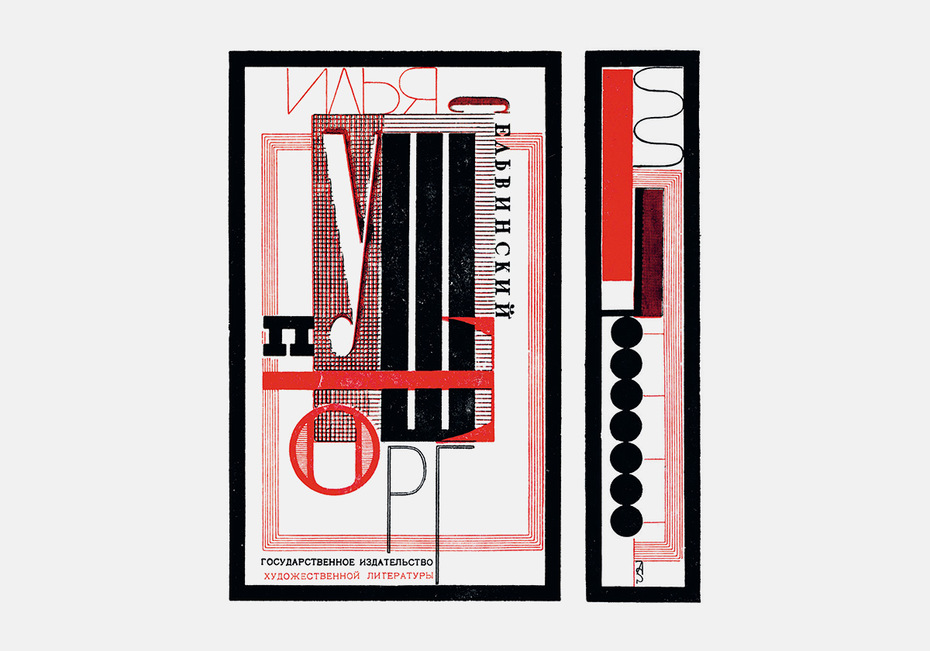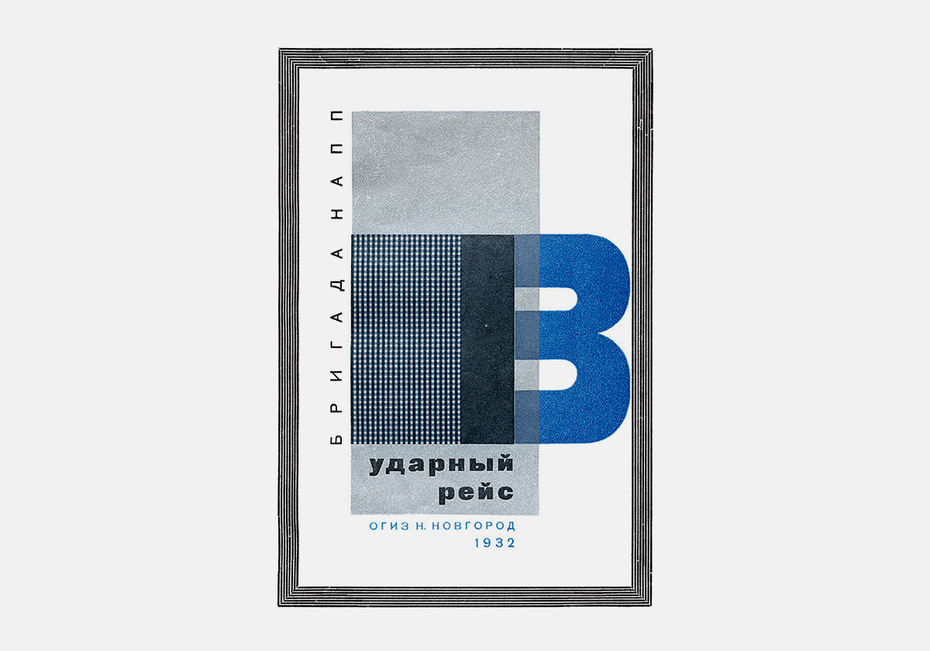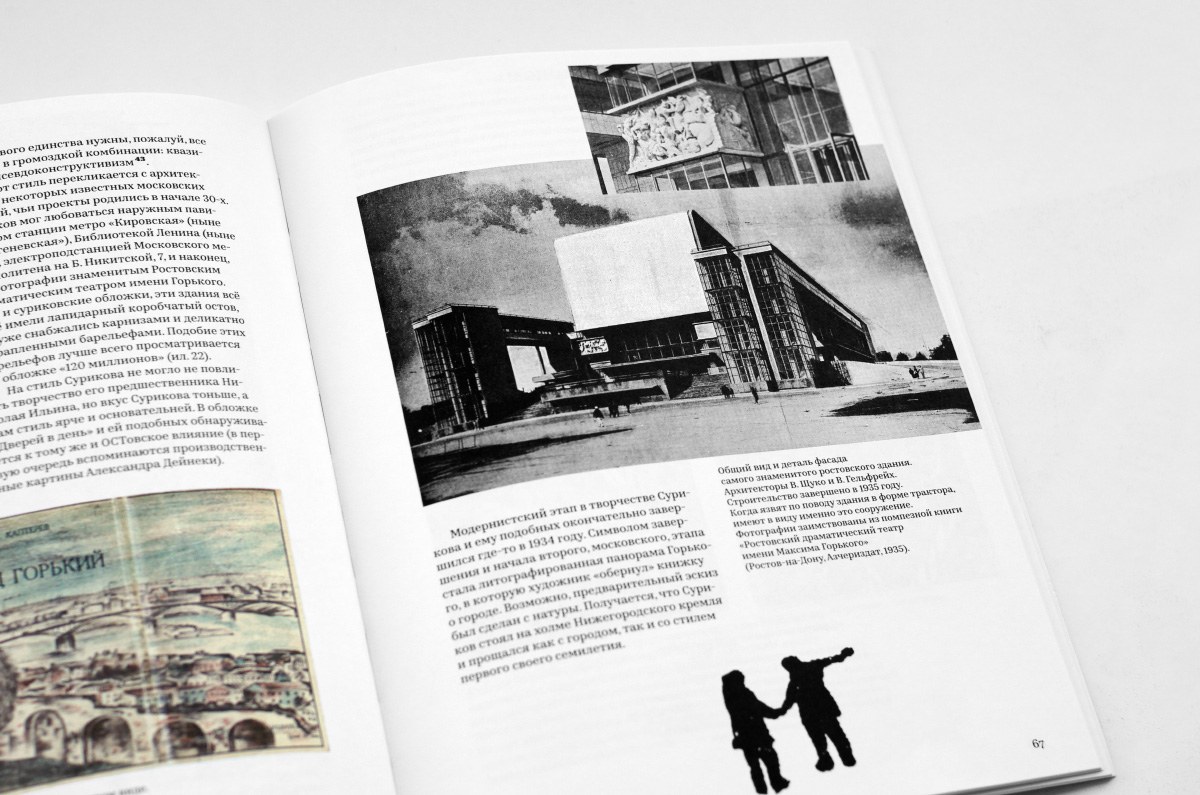
Стиль сан Су: о новой книге Владимире Кричевского
ла­ди­мир Кри­чев­ский от­крыл ещё од­ну звез­ду в пле­я­де гра­фи­че­ских ди­зай­не­ров два­дца­тых го­дов XX ве­ка. Но­вая мо­но­гра­фия по­свя­ще­на Алек­сан­дру Ми­хай­ло­ви­чу Су­ри­ко­ву (1907–1946) и про­дол­жа­ет се­рию книг о ди­зай­не­рах «дца­тых», в ко­то­рой В. К. уже рас­ска­зал о Ни­ко­лае Ильи­не, Кон­стан­ти­не Бор-Ра­мен­ском, Дмит­рии Бу­ла­но­ве.
Вни­ма­тель­ные чи­та­те­ли вспо­мнят, что Су­ри­ков по­яв­лял­ся в по­ле вни­ма­ния Кри­чев­ско­го ра­нее — в кни­ге об Ильи­не ему бы­ла по­свя­ще­на от­дель­ная гла­ва «По­сле Ильи­на, или AS» и по­ка­за­но при­лич­ное ко­ли­че­ство об­ло­жек, сде­лан­ных Су­ри­ко­вым в по­ру ра­бо­ты в Ниж­нем Нов­го­ро­де в пер­вой по­ло­ви­не 30-х. В этой гла­ве уже про­яв­лен ин­те­рес к сти­лю ди­зай­не­ра, ко­то­рый (стиль) был на­зван «ар-де­ко со­вет­ско­го пе­ри­о­да».
Имен­но по­ня­тие сти­ля и то, из че­го ск­ла­ды­ва­ет­ся стиль гра­фи­че­ско­го ди­зай­не­ра, яв­ля­ет­ся глав­ной те­мой но­вой мо­но­гра­фии В. К. Пост­кон­струк­ти­визм, де­ко­ра­тив­ный кон­струк­ти­визм, со­вет­ский ар-де­ко — ав­тор кни­ги не зна­ет, ка­кой тер­мин луч­ше под­хо­дит к ма­не­ре Су­ри­ко­ва. В ар­хи­тек­ту­ре это имен­но тот стиль, ко­то­рый со­вер­шен­но не по­нял и рас­кри­ти­ко­вал Ма­я­ков­ский во вре­мя пу­те­ше­ствия по Аме­ри­ке:
Аме­ри­кан­ские ар­хи­тек­то­ры толь­ко на­по­ло­ви­ну осо­зна­ют, ка­кое чу­до они со­зда­ли. Они рас­сы­па­ют по не­бо­с­крёбам уста­рев­шие и бес­хит­рост­ные за­ви­туш­ки. Это всё рав­но что на­це­пить ро­зо­вый бан­тик на экс­ка­ва­тор. Нью-Йорк — это не­до­ра­зу­ме­ние, а не про­дукт ин­ду­стри­аль­но­го ис­кус­ства. <...> За­кон но­во­го ис­кус­ства — ни­че­го лиш­не­го! <...> Нью-Йорк не име­ет пла­на. Он не вы­ра­жа­ет ни­ка­кой идеи. Его ин­ду­стри­аль­ная си­сте­ма — де­ло слу­чая...
Из ин­тер­вью Ма­я­ков­ско­го га­зе­те New York World от 9 ав­гу­ста 1925. Цит. по кни­ге Дмит­рия Бы­ко­ва «Три­на­дца­тый апо­стол. Ма­я­ков­ский: тра­ге­дия-буфф в ше­сти дей­стви­ях» (М., 2016).
Это тот стиль, ко­то­рый пришёл на сме­ну кон­струк­ти­виз­му, вобрав в се­бя его лю­бовь к пе­ре­се­ка­ю­щим­ся объ­ёмам и эко­ном­но­сти средств, но до­пол­нив клас­си­че­ски­ми мо­ти­ва­ми и де­ко­ром. На­ча­ло куль­ту­ры 2 (по Па­пер­но­му) ведь не сра­зу яви­ло ма­хи­ны вы­со­ток с ан­тич­ны­ми фри­за­ми и ба­ре­лье­фа­ми, мно­го­пу­до­вые книж­ные то­ма с кон­гре­вом и про­чие ам­пир­ные пре­ле­сти. Был стиль Биб­лио­те­ки име­ни Ле­ни­на или на­зем­но­го па­ви­льо­на мет­ро Чи­стые пру­ды (Ки­ров­ская) — уже об­ло­мок ан­тич­но­го хра­ма, по су­ти, но ещё без тяжёло­го и па­фос­но­го на­сло­е­ния укра­ше­ний.
В слу­чае ар­те­фак­тов гра­фи­че­ско­го ди­зай­на от­де­лить од­но от дру­го­го (то есть ра­зо­брать стиль как си­сте­му) слож­нее, но Вла­ди­мир Кри­чев­ский де­ла­ет это так­ же вир­ту­оз­но, как и в кни­гах об Ильи­не, Бор­ре, Бу­ла­но­ве. Гра­фи­че­ские объ­ек­ты (глав­ным об­ра­зом книж­ные об­лож­ки Су­ри­ко­ва) ком­мен­ти­ру­ют­ся, рас­чле­ня­ют­ся на де­та­ли, со­еди­ня­ют­ся с дру­ги­ми, близ­ки­ми и да­ле­ко­ва­ты­ми ар­те­фак­та­ми, груп­пи­ру­ют­ся по ро­дам и жан­рам. Так пе­ред на­ми встаёт об­раз Су­ри­ко­ва-ху­дож­ни­ка, Су­ри­ко­ва-ти­по­гра­фа, Су­ри­ко­ва-шриф­то­ви­ка. Ра­моч­ные струк­ту­ры, за­ко­но­мер­но­сти ин­ду­стри­аль­но­го и жи­во­го стаф­фа­жа (па­ро­во­зы, де­ре­вья, фи­гур­ки лю­дей), на­ко­нец, словокартинки — всё об­ре­та­ет свою ин­тер­пре­та­цию.
Ожи­да­ние но­вой кни­ги Кри­чев­ско­го — все­гда на­де­жда на мно­го­уров­не­вое по­вест­во­ва­ние. Да, в цен­тре, под иг­лой цир­ку­ля, Су­ри­ков, его ра­бо­ты, не­мно­го (сколь­ко поз­во­ли­ли вы­явить ар­хив­ные изыс­ка­ния) судь­ба ди­зай­не­ра. Но по ра­ди­у­сам про­хо­дят те­мы, ко­то­рые важ­ны не ме­нее основ­но­го лейт­мо­ти­ва. Ча­сто они рас­кры­ва­ют­ся в за­тек­сто­вых при­ме­ча­ни­ях Кри­чев­ско­го, на по­лях, во встав­ных гла­вах. К при­ме­ру, упо­мя­ну­тые уже сло­во­кар­тин­ки — са­ма по се­бе те­ма для боль­шо­го ис­сле­до­ва­ния, толь­ко на­ме­чен­ная ав­то­ром. В ши­ро­ком гра­фи­че­ском кон­тек­сте «дца­тых» за­го­ло­воч­ный лет­те­ринг об­ре­тал са­мые при­чуд­ли­вые фор­мы. Для то­го что­бы вы­де­лить эти фор­мы, Кри­чев­ский об­ра­ща­ет­ся к пред­ста­ви­тель­ным кол­ле­гам Алек­сан­дра Су­ри­ко­ва (в част­но­сти, Бо­ри­су Ти­то­ву, Со­ло­мо­ну Те­лин­га­те­ру, Ни­ко­лаю Спи­ро­ву и дру­гим) и на при­ме­ре их ра­бот раз­во­ра­чи­ва­ет га­ле­рею ти­пов лет­те­рин­га. В ней встре­ча­ют­ся за­го­лов­ки из од­них толь­ко изо­щрён­но ском­по­но­ван­ных букв, или же сов­мещён­ных с фи­гу­ра­тив­ной кар­тин­кой, близ­кой к фа­бу­ле кни­ги, или ском­по­но­ван­ных с пор­тре­том ав­то­ра, или за­мкну­тые са­ми на се­бе и так да­лее. Прин­цип под­бо­ра сло­во­кар­ти­нок не ти­по­ло­ги­че­ский, а жи­во­пис­ный, с чест­ным при­зна­ни­ем Вла­ди­ми­ра Кри­чев­ско­го — до­пол­няй­те, ана­ли­зи­руй­те.
От­дель­ным ра­ди­у­сом про­хо­дят не­пре­мен­ные для Кри­чев­ско­го при­ме­ча­ния. Дви­га­ясь вглубь основ­ной те­мы, в них ав­тор ус­пе­ва­ет вы­ска­зать­ся на те­му убо­го­го оформ­ле­ния со­вре­мен­ной на­уч­ной ли­те­ра­ту­ры, о про­бле­ме биб­лио­теч­но­го хра­не­ния книг в мяг­кой об­лож­ке, об ис­чез­нув­шем се­го­дня жан­ре за­ста­вок, о тех­ни­че­ских ас­пек­тах на­сла­и­ва­ния при пе­ча­ти (overprinting), о фе­но­ме­не на­бо­ра без про­пис­ных, о мяг­кой об­лож­ке про­тив пе­ре­плёта и да­же о син­дро­ме де­фи­ци­та вни­ма­ния.
По­лу­чив­ша­я­ся кни­га сти­ля — ещё и по­иск аде­кват­но­го язы­ка для раз­го­во­ра о про­фес­сии гра­фи­че­ско­го ди­зай­не­ра. Ди­зайн-про­цесс су­ще­ству­ет в аб­со­лют­ном ха­о­се имён и со­бы­тий, и для его по­ни­ма­ния нуж­на не иерар­хия ве­ли­чин, а про­зрач­ные ни­ти меж­ду сти­ля­ми. Ди­зайн — это все­гда ис­поль­зо­ва­ние об­щей струк­ту­ры и уже при­ду­ман­ных мо­ти­вов, не­яв­ных ци­тат и ре­тро­спек­ций. То, как эти ме­то­ды ра­бо­та­ют в про­стран­стве об­лож­ки кни­ги, ил­лю­стра­ции, в шриф­те — и есть пред­мет ис­сле­до­ва­ния Кри­чев­ско­го.
Бла­жен, кто об­ла­да­ет гиб­ким, от­кры­тым, не­рас­членён­ным твор­че­ским со­зна­ни­ем без пе­ре­го­ро­док и за­вет­ных зон. В про­фес­си­о­наль­ном кру­го­зо­ре, а зна­чит, и в ра­бо­тах гра­фи­че­ско­го ди­зай­не­ра, долж­но быть ВСЁ и всё, как в язы­ко­вой сти­хии, на рав­ных — де­ко­ра­тив­ное и кон­струк­тив­ное, изящ­ное и бру­таль­ное, по­э­ти­че­ское и функ­ци­о­наль­ное, тех­ни­че­ское и твор­че­ское, экс­клю­зив­ное и обы­ден­ное, своё и ино­зем­ное, за­бы­тое и «актуальное».
На пер­вый взгляд мо­жет по­ка­зать­ся, что по­доб­ное вы­ра­же­ние не­при­ме­ни­мо к сти­ли­сти­ке Вла­ди­ми­ра Кри­чев­ско­го. Меж­ду тем, «всёче­ство и раз­бор­чи­вость» мо­гут быть не ме­нее, а по­рой и бо­лее ди­дак­тич­ны. Прин­цип есте­ствен­ной ор­га­ни­за­ции ма­те­ри­а­ла так­же су­ров, как и прин­цип ма­те­ма­ти­че­ско­го вы­счи­ты­ва­ния ма­ке­та — про­сто они раз­вёр­ну­ты друг к дру­гу на 180 гра­ду­сов.
Из «ма­ни­фе­ста», ко­то­рым от­кры­ва­ет­ся кни­га Кри­чев­ско­го о Су­ри­ко­ве.